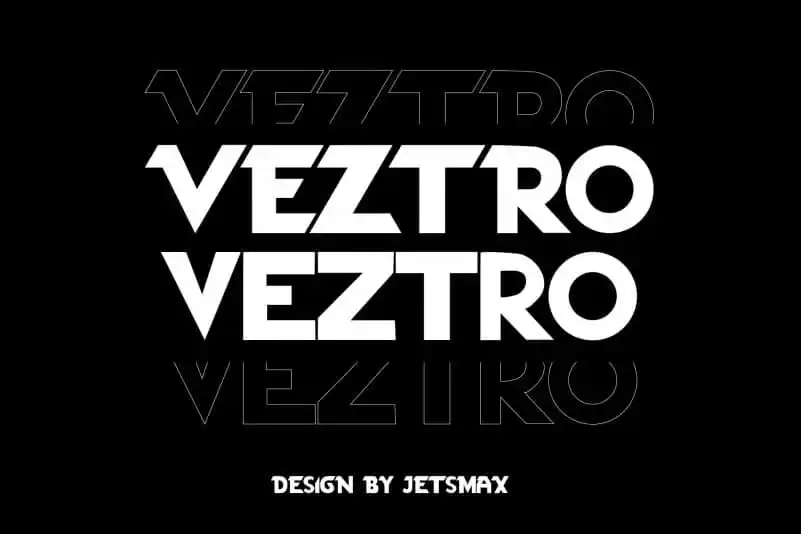
Veztro Display Font – Download Grátis
A Veztro Display Font é uma fonte de exibição moderna que traz uma pitada futurista para seus projetos. Ideal para quem busca dar um toque leve e alegre, essa fonte se destaca como uma excelente escolha para qualquer projeto que deseje uma aparência mais animada. Seu designer, jetsmax, criou uma solução perfeita para aqueles que querem destacar sua mensagem ou produto de maneira chamativa e inovadora. A Veztro é uma excelente adição à sua coleção de fontes, tornando-a a escolha perfeita para quem busca um look atemporal mas sempre atual em seus projetos digitais.